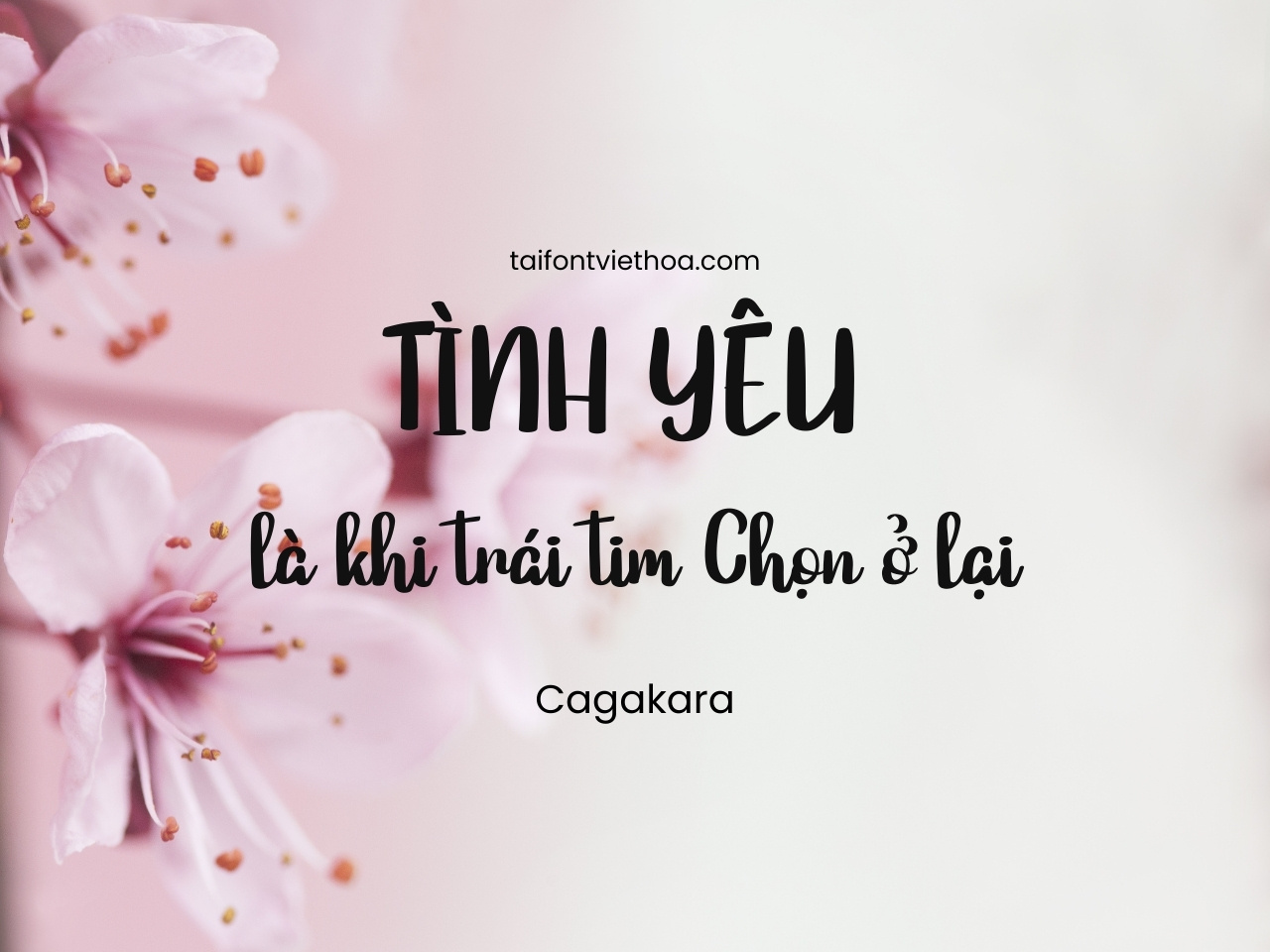
Giới thiệu font Cagakara – Kiểu chữ ký ngẫu hứng từ Eknoji
Cagakara là một font chữ ký mang phong cách viết tay hiện đại, được thiết kế bởi Eknoji – một nhà sáng tạo nổi bật trong lĩnh vực font script cá nhân hóa. Font này thể hiện rõ tinh thần tự do, đầy cảm xúc và nghệ thuật qua từng nét chữ. Với đường nét mềm mại nhưng có điểm nhấn rõ ràng, Cagakara được sử dụng rộng rãi trong các thiết kế cần sự thanh lịch và cá tính. Phiên bản Việt hóa hiện đã hỗ trợ đầy đủ tiếng Việt và hơn 90 ngôn ngữ khác nhờ hệ ký tự mở rộng, mang lại sự linh hoạt trong ứng dụng. Font đã được taifontviethoa.com sưu tầm và chọn lọc kỹ lưỡng, nhằm hỗ trợ các nhà thiết kế sáng tạo trong những dự án branding cá nhân, sản phẩm thủ công và truyền thông tình cảm.
Vẻ đẹp thiết kế tinh tế và ứng dụng của Cagakara
Cagakara sở hữu cấu trúc chữ bay bổng với các đường nét mảnh và gãy gọn, mang đến cảm giác như một chữ ký đầy cảm xúc và độc đáo. Các ký tự được kết nối một cách uyển chuyển, tạo sự liền mạch cho tổng thể. Font đi kèm với các ligatures và ký tự thay thế giúp tăng độ tùy biến và cá nhân hóa trong từng thiết kế. Cagakara là lựa chọn hoàn hảo cho các dự án như thiệp cưới, tiêu đề blog, logo cá nhân, poster lễ tình nhân, sản phẩm thời trang hoặc thiết kế liên quan đến hình ảnh cưới hỏi. Đặc biệt phù hợp với ngành quảng cáo, ẩm thực, studio ảnh cưới và các dịp lễ hội như Valentine, sinh nhật, lễ kỷ niệm.